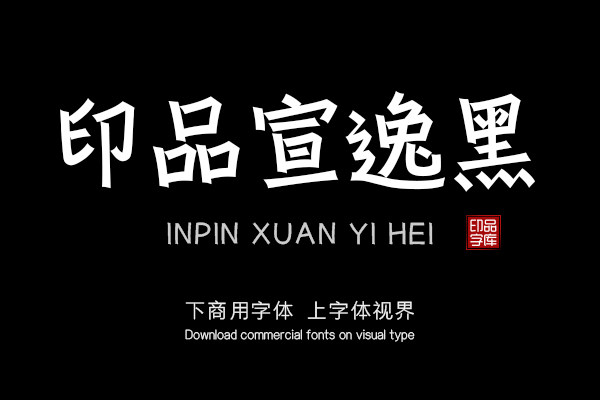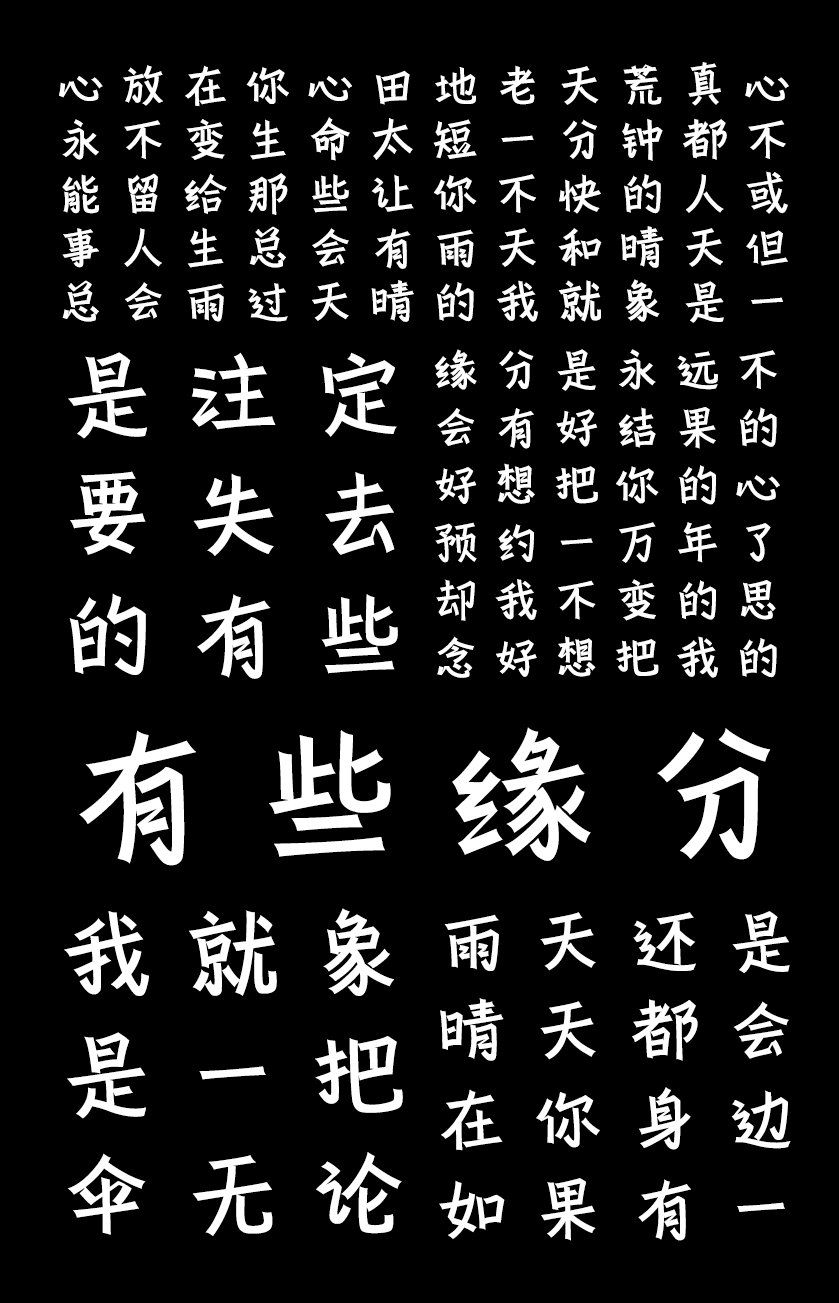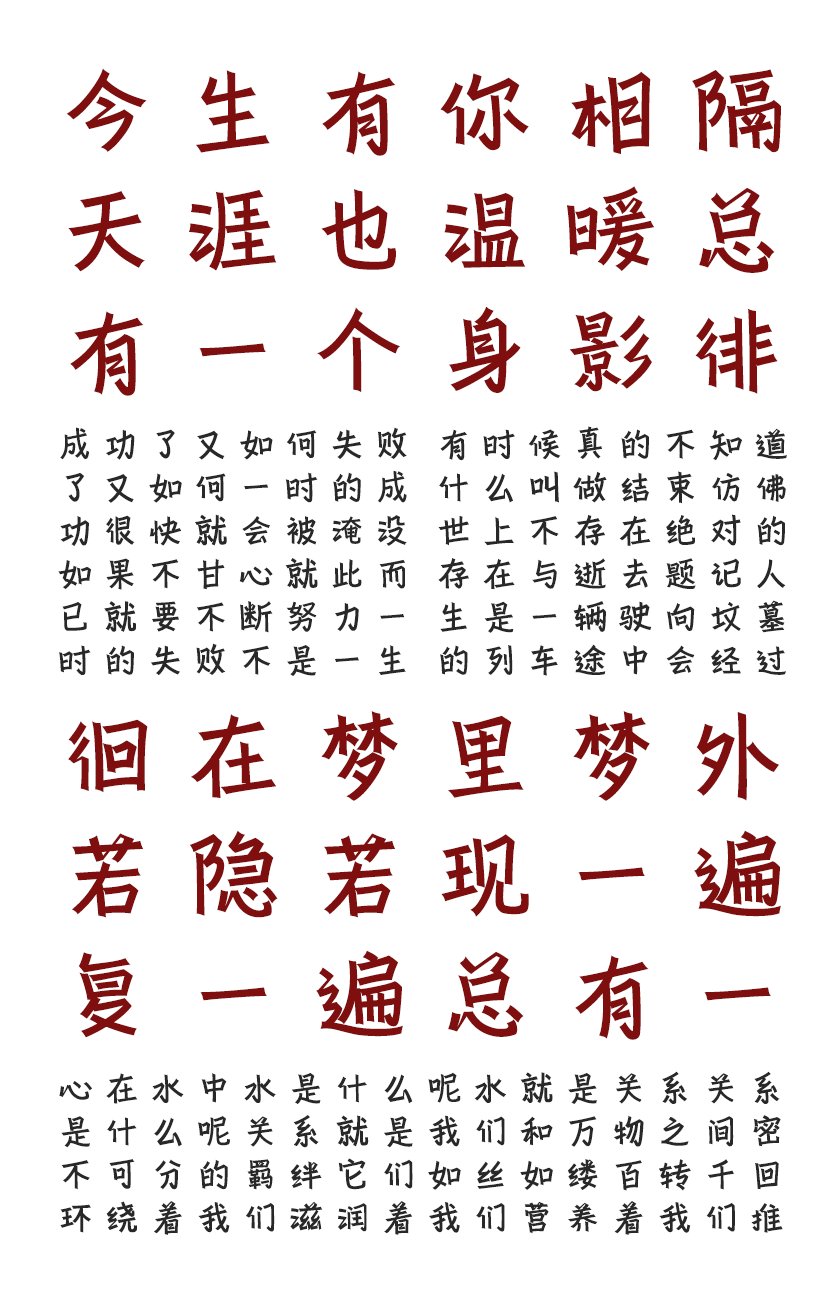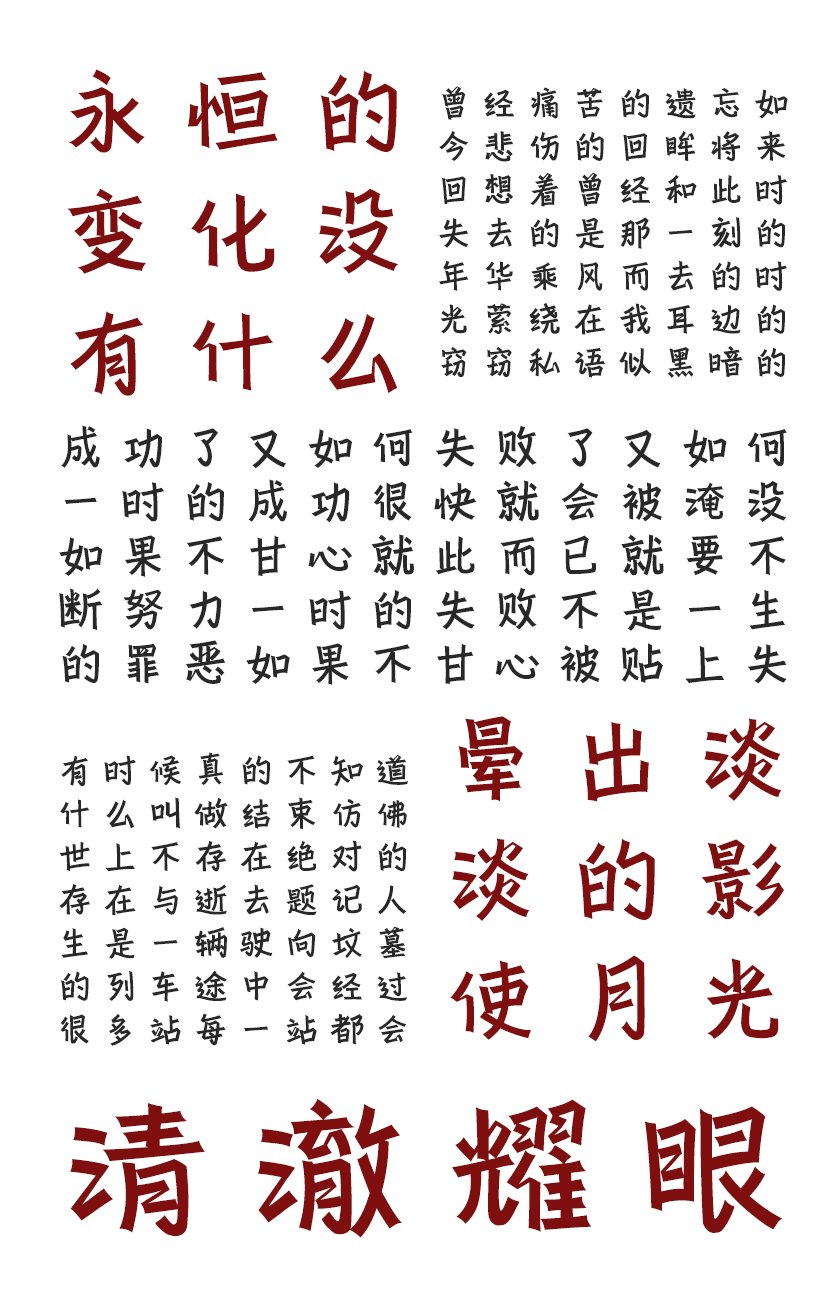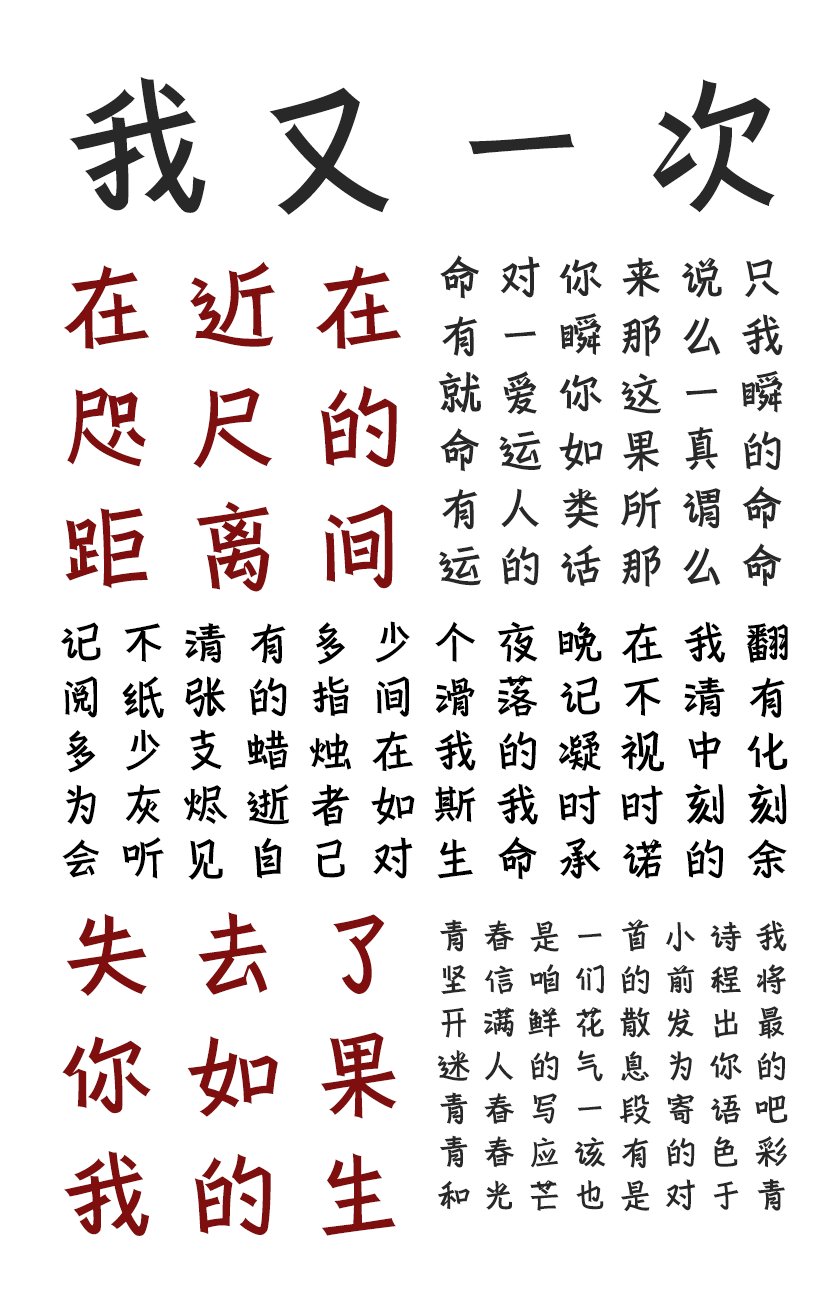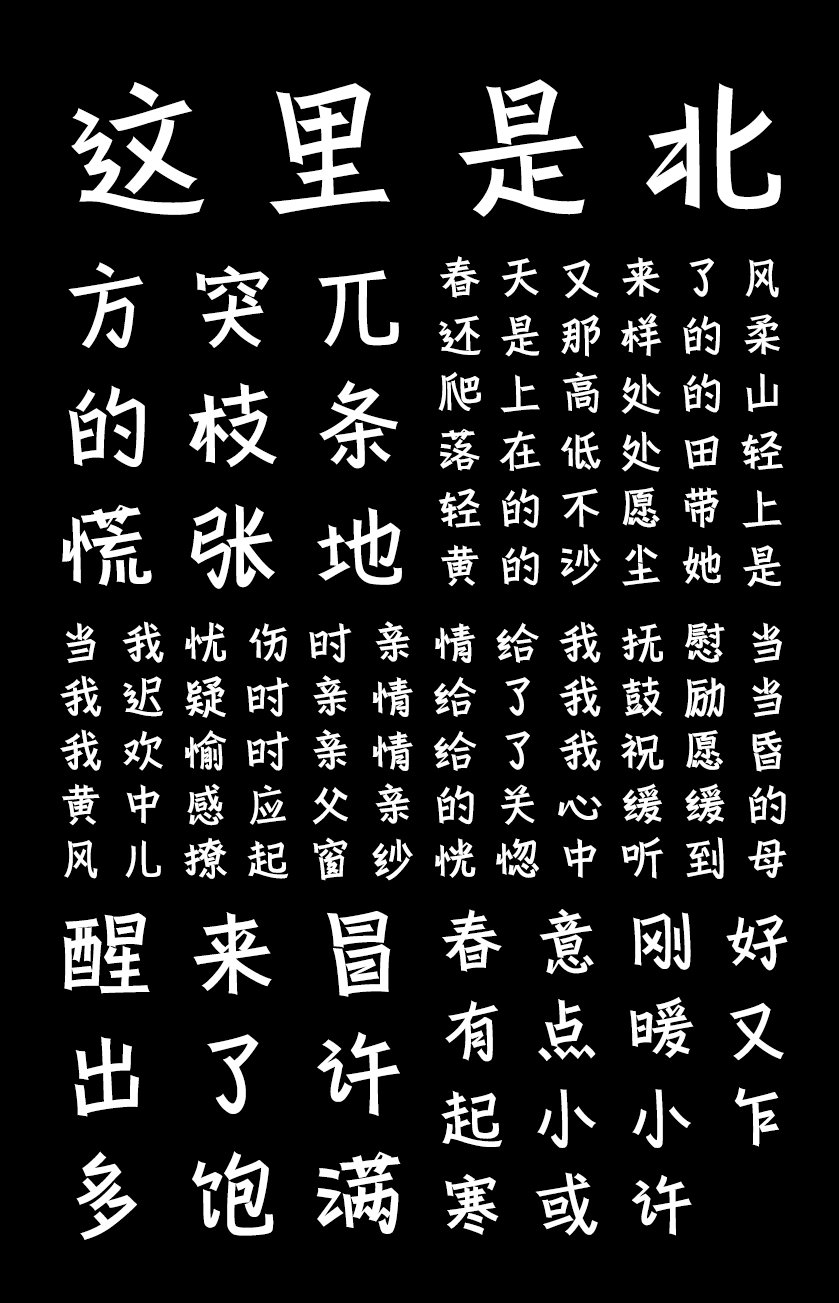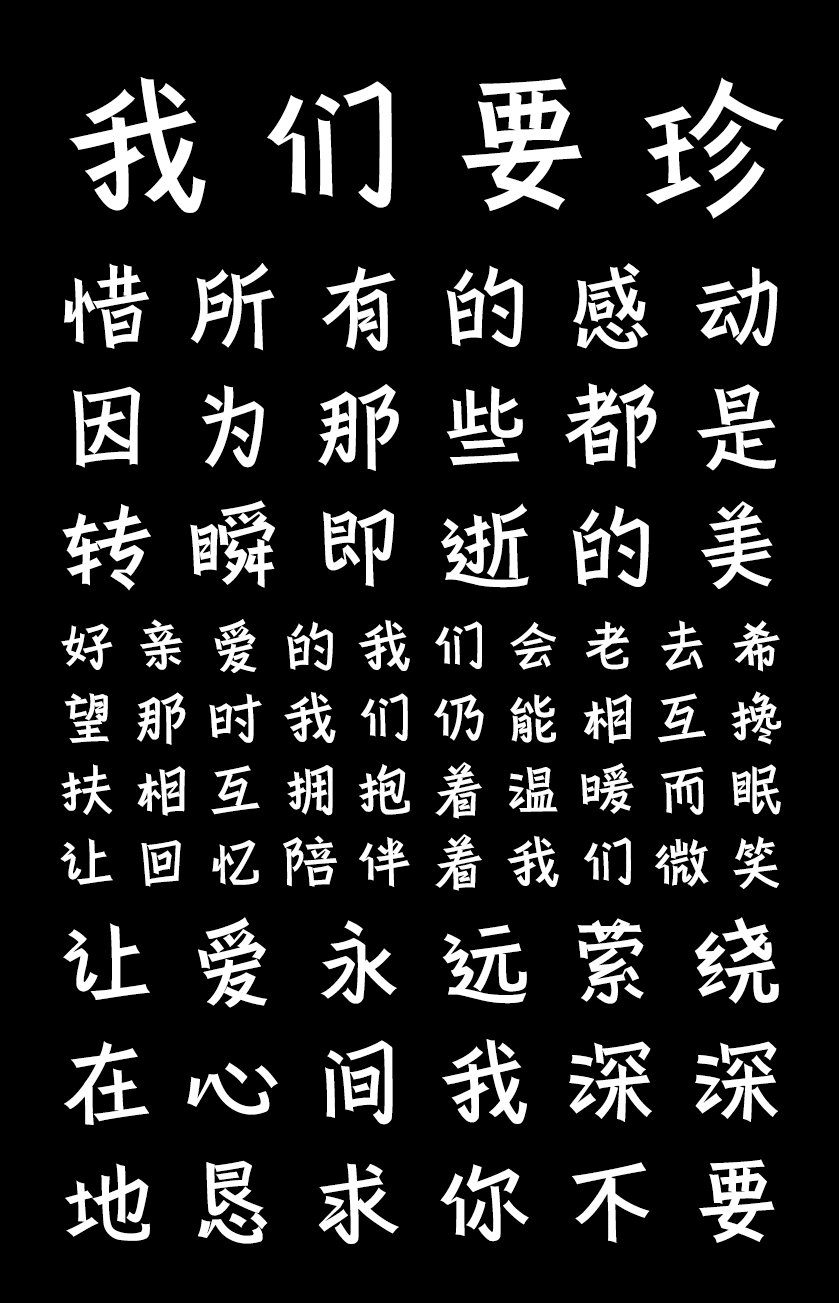
• 印品宣逸黑
• 印品宣逸黑兼顾印刷字体规整的同时又融入像手写扁头体的随性的笔画,造型俊美适意,有较好的的展示效果。这款字结体顾盼呼应,笔画相互穿插避让,字型笔画错落有致,潇洒肆意,行云流水间,泼墨如洒酒。横笔画左侧倾斜的手法在黑体稳重大气的字形中增添少许灵动;印品宣逸黑这款字体字面较大,整体感觉大气。具有良好的视觉审美和阅读效果,不管使用用于产品包装还是标题字样,都有不错的展示效果。